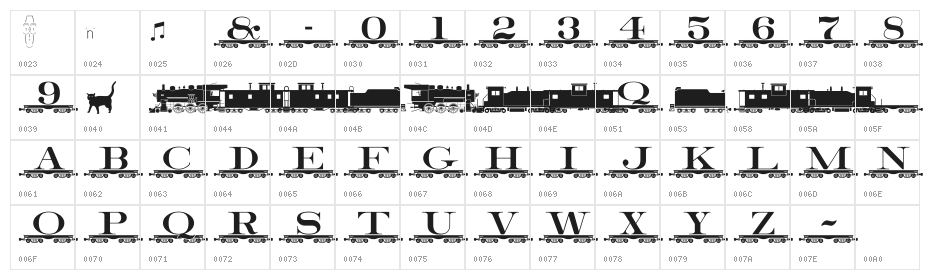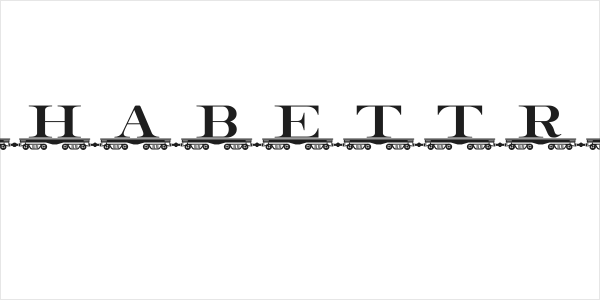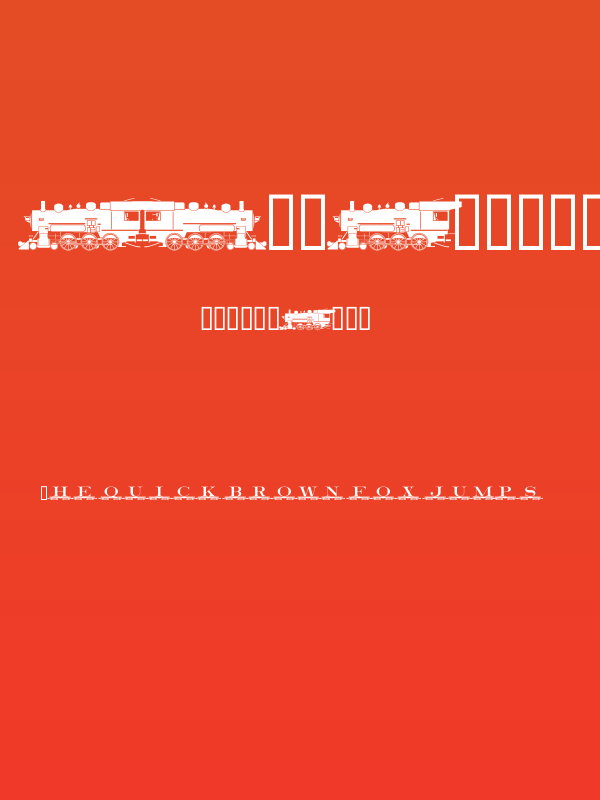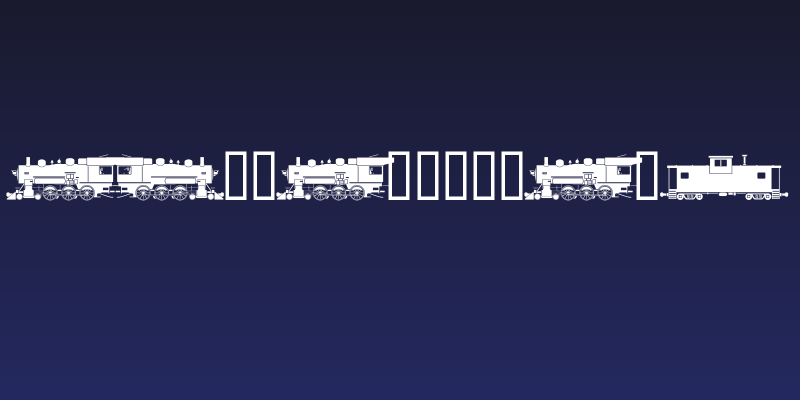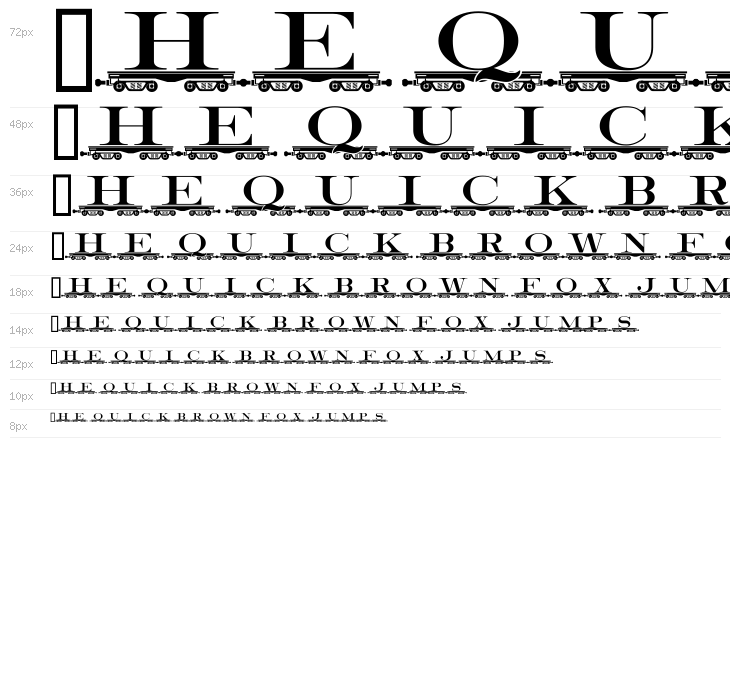
alphabettrain Font
| Caz de utilizare | Headlines, Logos, Themed Designs |
| Proiecte propuse | Ideal for children's books, educational materials, themed party invitations, and playful branding projects. |